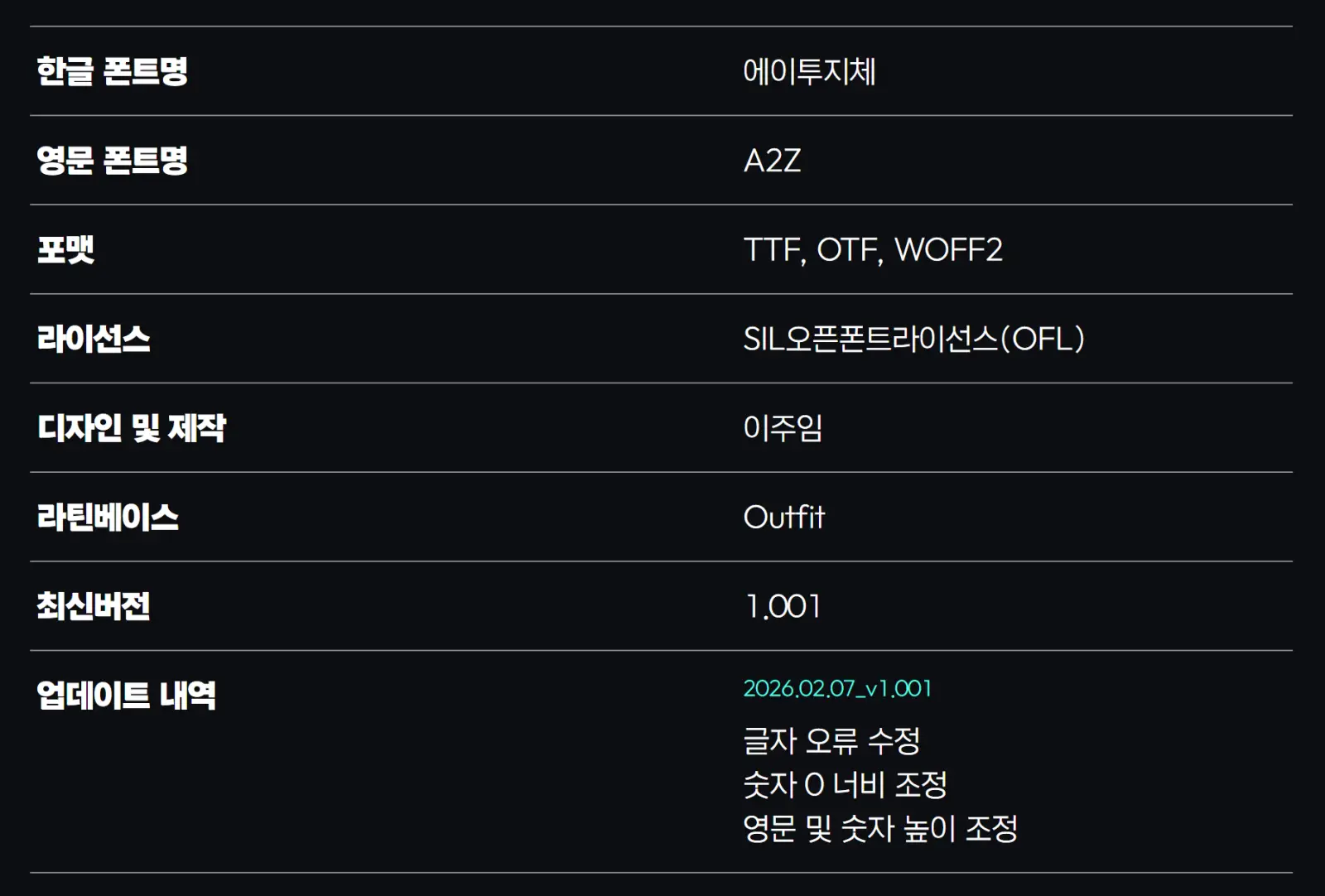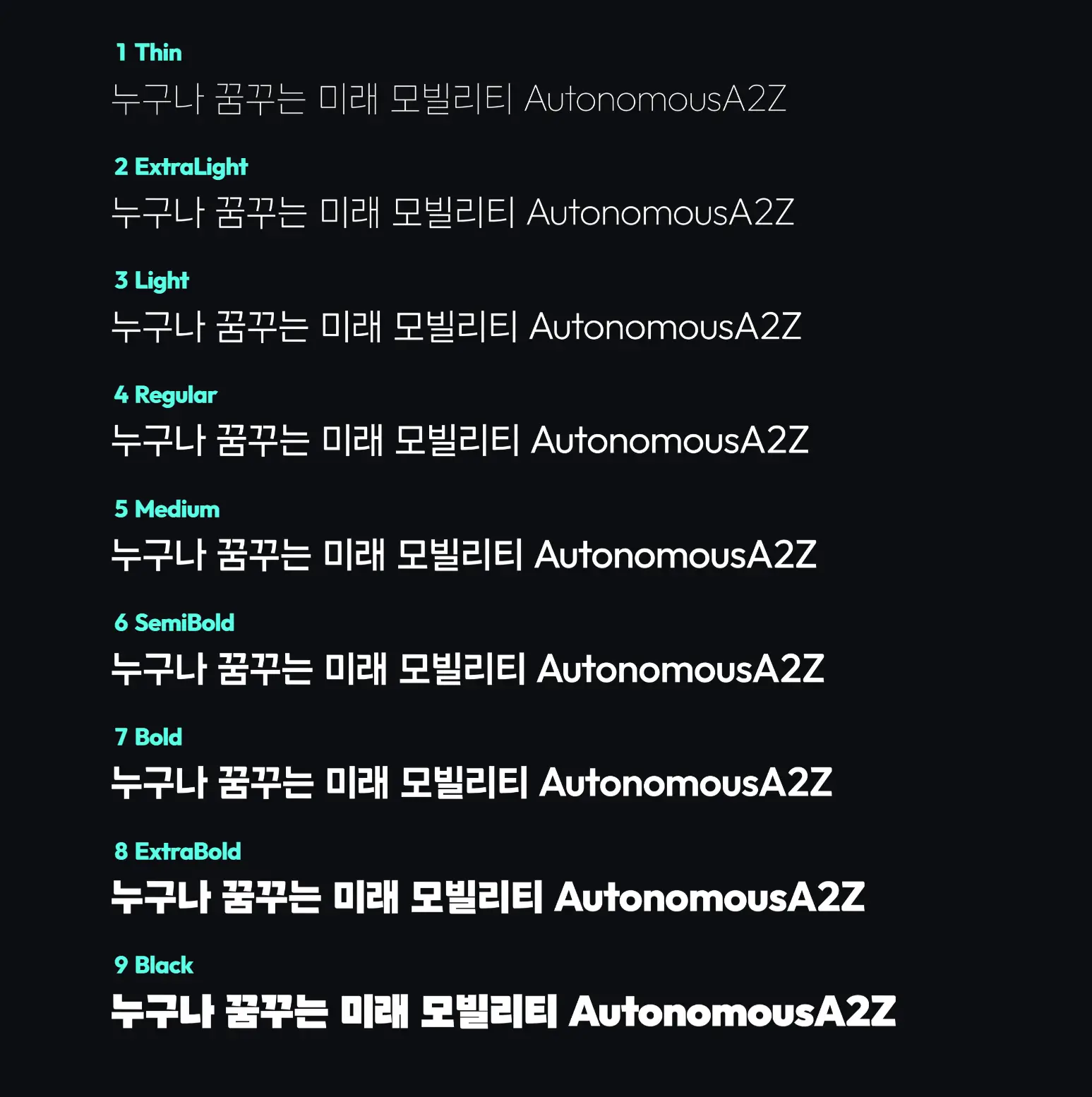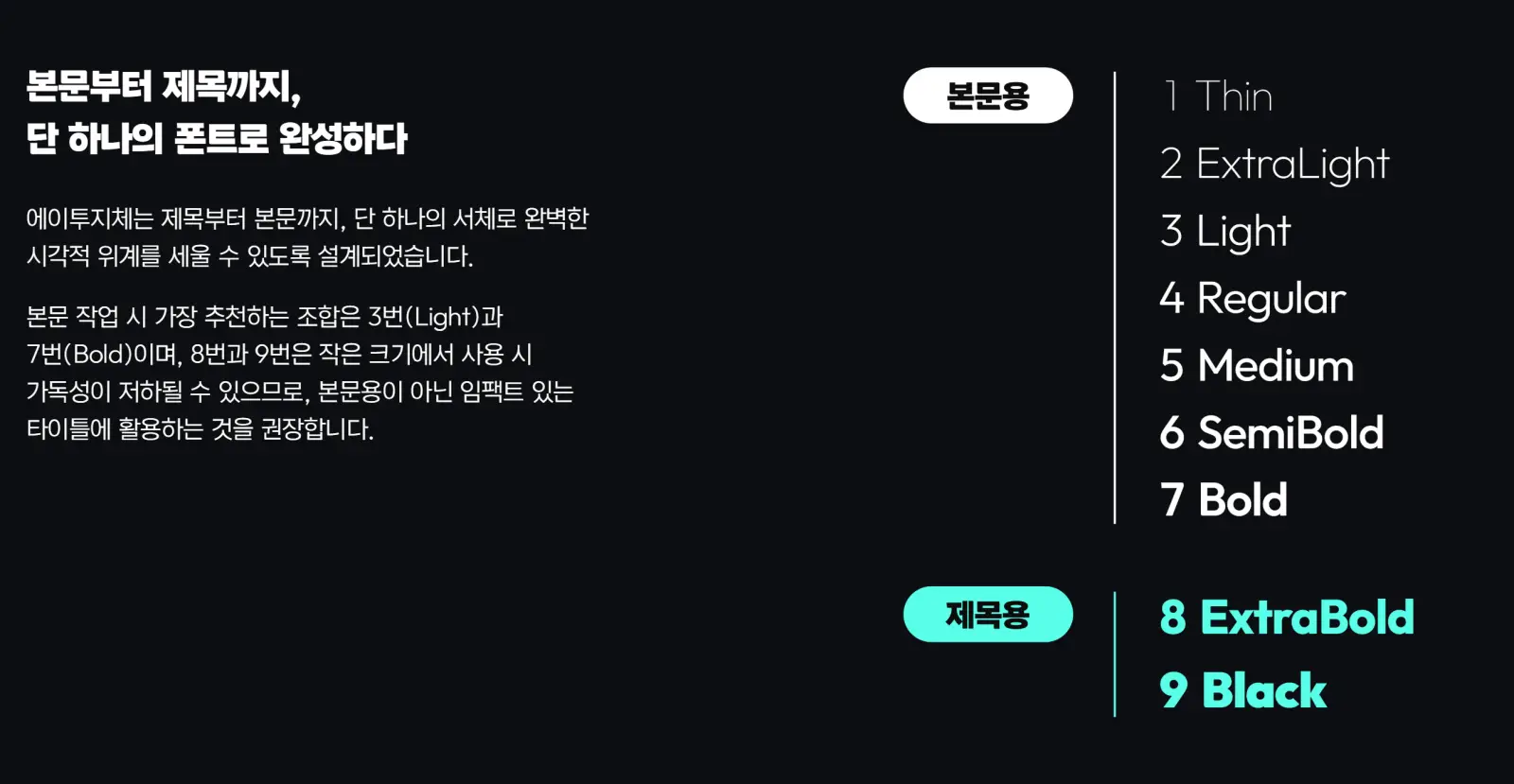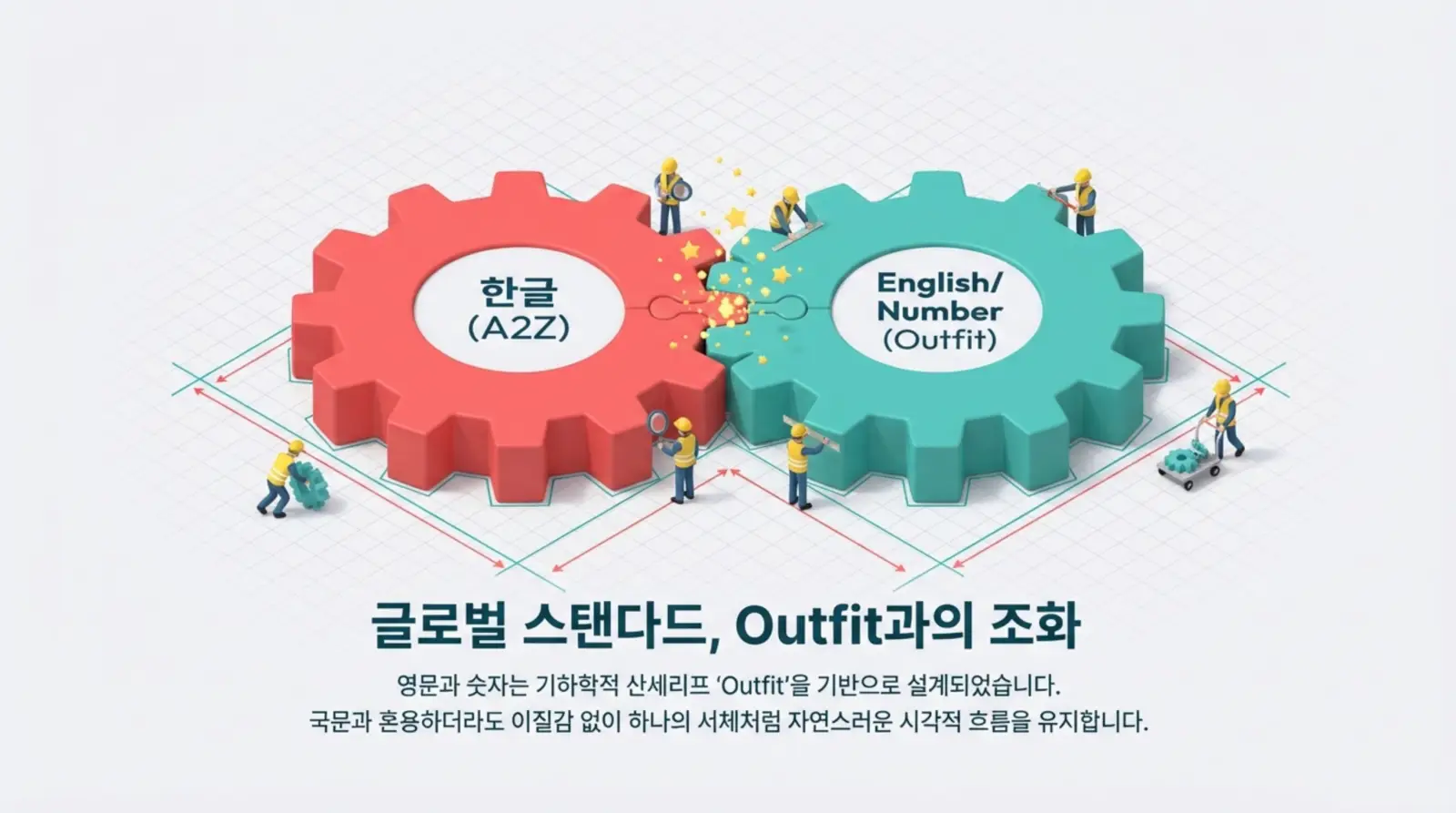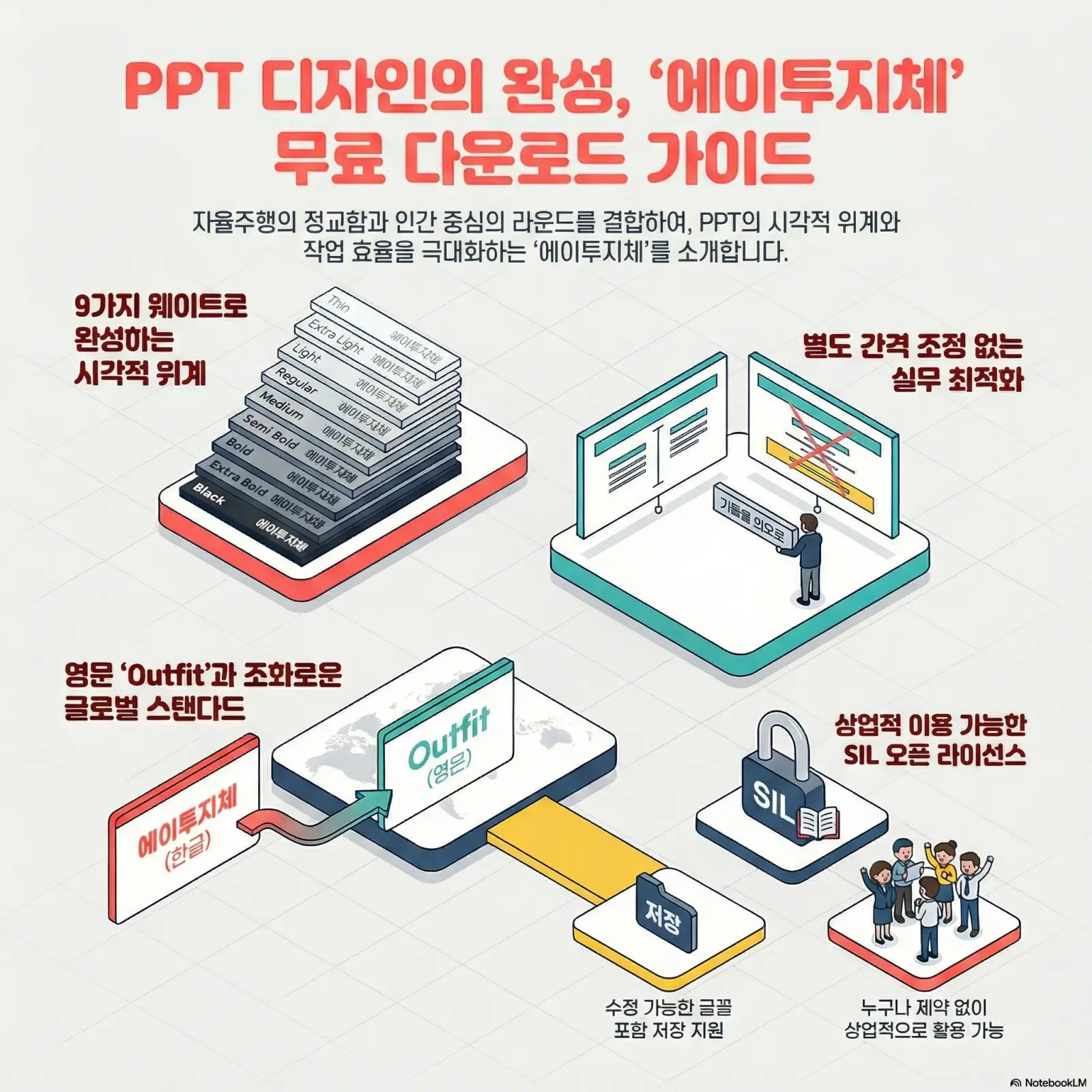
파워포인트용 무료 폰트 추천 – 에이투지체 다운로드
“발표 자료의 완성도는 ‘폰트’에서 시작됩니다.”
수많은 파워포인트 템플릿보다 중요한 것은 가독성과 신뢰감을 동시에 줄 수 있는 서체의 선택입니다. 오늘은 자율주행 기술의 정교함과 인간 중심의 따뜻함을 담은 역대급 무료 서체, ‘에이투지체(A2Z)’를 완벽 분석하고 설치 방법부터 활용 꿀팁까지 모두 공유합니다. 지금 바로 확인해 보세요!
그런데 이번에 정말 물건 하나가 나왔습니다. 바로 대한민국 자율주행의 자부심이라 불리는 ‘오토노머스에이투지’에서 공개한 ‘에이투지체’입니다. 단순히 글자만 예쁜 게 아니라, 실무자의 편의성을 극대화한 기능들이 꽉꽉 채워져 있어서 여러분께 소개하지 않을 수가 없더라고요. 자, 그럼 8,000자 분량의 심층 분석, 지금부터 시작합니다! 😊
1. 에이투지체(A2Z)는 어떤 서체인가요? 🤔
에이투지체는 알파벳의 시작인 A부터 마지막인 Z까지, 그리고 숫자 0에서 9까지 어떤 조합에서도 흐트러짐 없는 완벽한 균형을 목표로 설계되었습니다. 이 서체의 가장 큰 조형적 특징은 바로 ‘사선’과 ‘라운드’의 조화입니다. 첨단 기술을 상징하는 날카로운 사선과 인간 중심의 가치를 담은 부드러운 라운드가 만나, 막연한 미래 비전이 아닌 현재진행형인 자율주행의 실체를 형상화했죠.
실제로 글자를 가만히 들여다보면, 기계적인 차가움보다는 실질적인 안전과 기술적 완결성이 동시에 느껴집니다. 이는 오토노머스에이투지가 추구하는 ‘완성형 모빌리티 솔루션’의 가치를 서체에 그대로 투영했기 때문입니다. 폰트 하나에도 기업의 철학이 담겨 있다는 점이 정말 놀랍지 않나요?
💡 여기서 잠깐! 에이투지체의 탄생 배경
이 서체는 이미 ‘프리젠테이션’과 ‘페이퍼로지체’로 수많은 팬을 보유한 디자이너 ‘이주임’님이 직접 설계했습니다. 오픈소스를 결합했던 이전 작업과 달리, 이번에는 한글 전체를 직접 설계하여 그 의미가 더욱 남다르다고 하네요.
2. 실무자를 감동시킨 ‘역대급’ 특징 📊
① 본문부터 제목까지, 9가지 웨이트의 힘
보통 무료 폰트는 웨이트(굵기)가 2~3종류인 경우가 많아 아쉬웠죠? 에이투지체는 무려 9가지 패밀리(Thin, ExtraLight, Light, Regular, Medium, SemiBold, Bold, ExtraBold, Black)를 지원합니다. 이 덕분에 단 하나의 서체만으로도 PPT 내에서 완벽한 시각적 위계를 세울 수 있습니다.
② 굵기에 따라 달라지는 정교한 비례 설계
이 부분이 제가 가장 소름 돋았던 포인트인데요, 에이투지체는 단순히 선의 굵기만 키운 게 아닙니다. 가늘 때는 날렵한 ‘장체’ 스타일로, 두꺼워질수록 안정적인 ‘정체’ 스타일로 글자의 가로 폭이 점진적으로 확장됩니다. 이런 보정 덕분에 어떤 웨이트를 써도 시각적 무게 중심이 일정하게 유지되어 레이아웃이 매우 조화롭습니다.
③ 수직 중앙 정렬의 해방
PPT에서 도형 안에 글자를 넣고 ‘상하 정렬’ 맞추느라 스트레스받으신 적 많으시죠? 에이투지체는 도형 안에서 별도의 간격 조정 없이도 완벽한 수직 중앙에 위치하도록 설계되었습니다. 심지어 취소선과 형광펜의 중심까지 정교하게 맞춰져 있어 편집 효율이 비약적으로 상승합니다.
3. 영문과 숫자의 완벽한 조화, ‘Outfit’ 기반 🧮
한글 폰트를 쓸 때 가장 거슬리는 게 뭔지 아세요? 바로 ‘영문과 숫자가 따로 노는 느낌’입니다. 에이투지체는 글로벌 스탠다드 서체인 ‘Outfit’을 기반으로 영문과 숫자를 디자인했습니다.
현대적이고 기하학적인 Outfit의 인상을 한글 조형에 맞춰 정교하게 다듬었기 때문에, 국문과 영문을 혼용해도 이질감이 전혀 없습니다. 특히 수치가 중요한 데이터 슬라이드에서 이 서체의 진가가 발휘되죠. 숫자 0의 너비와 영문 높이까지 세밀하게 보정된 1.001 최신 버전을 경험해 보세요.
에이투지체 핵심 요약
✨ 압도적 다양성: 9가지 웨이트 제공으로 폰트 하나로 디자인 끝!
📊 정교한 설계: 굵기에 따라 자폭이 변하는 마법 같은 비례
🚀 실무 최적화: 도형 내 수직 중앙 정렬 자동화로 작업 시간 단축
자율주행의 정밀함과 인간의 따뜻함을 담은 서체로 여러분의 가치를 전달하세요.